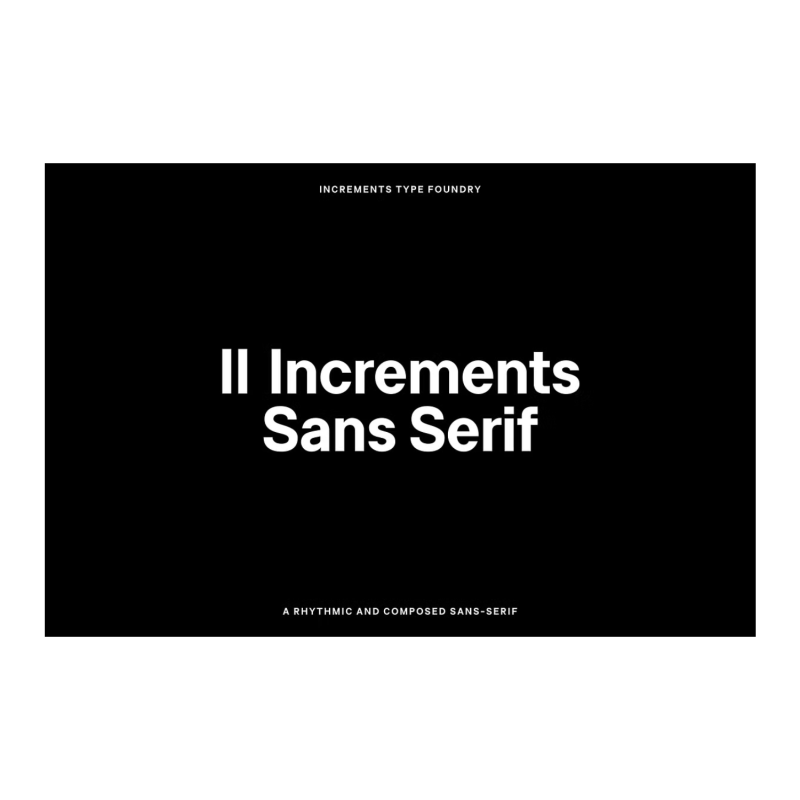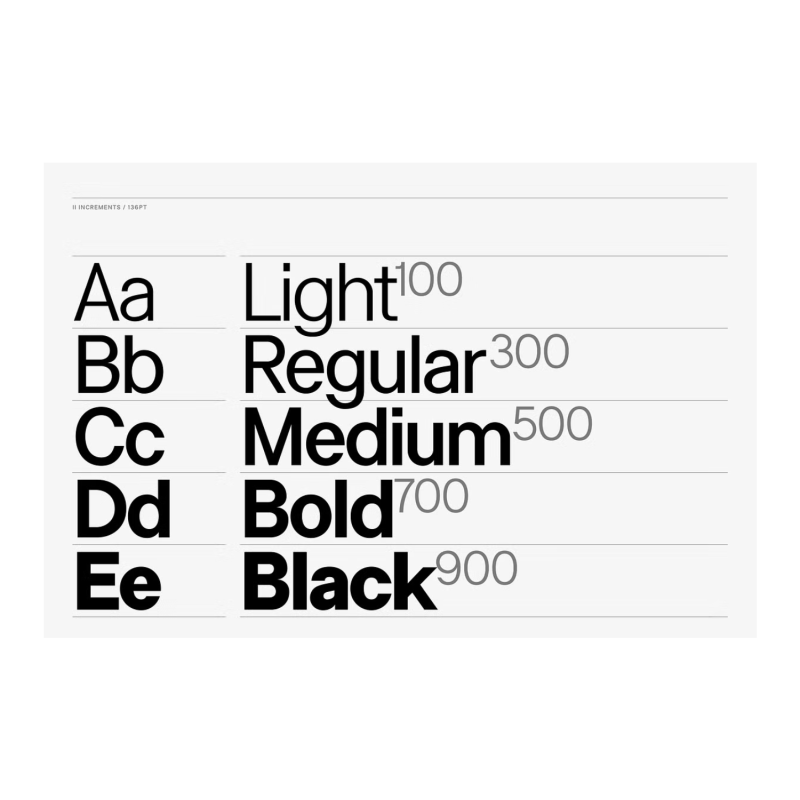
الزيادات الثانية: خط بلا رقيق
مستنيرة بالنسب والمبادئ الكلاسيكية الغريبة في النظرية الموسيقية ، ينتج عن II Increments Sans إيقاعي ومؤلف sans-serif. داخل شبكة منظمة ، يسمح التجويد والانسجام بين مبادئها الوظيفية وخصائصها العاطفية بالاستخدام في كل من أحجام النص والعرض.